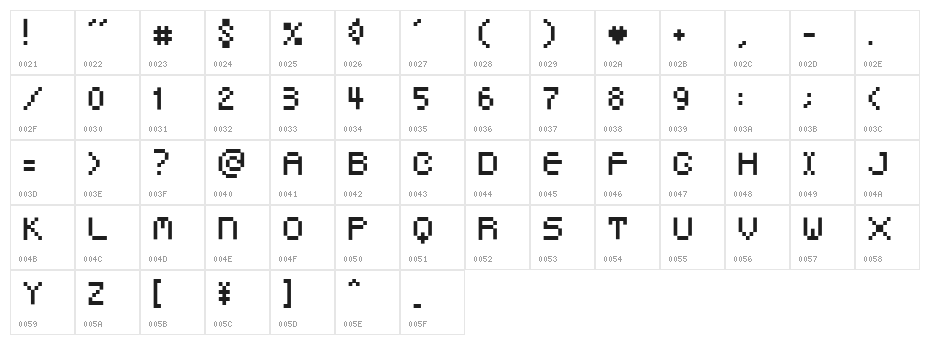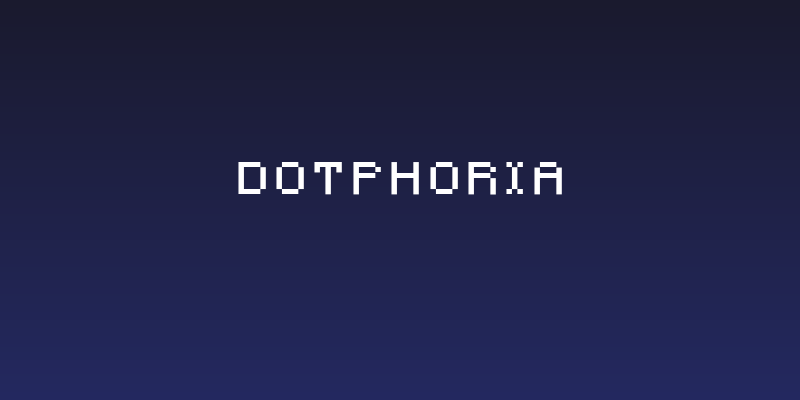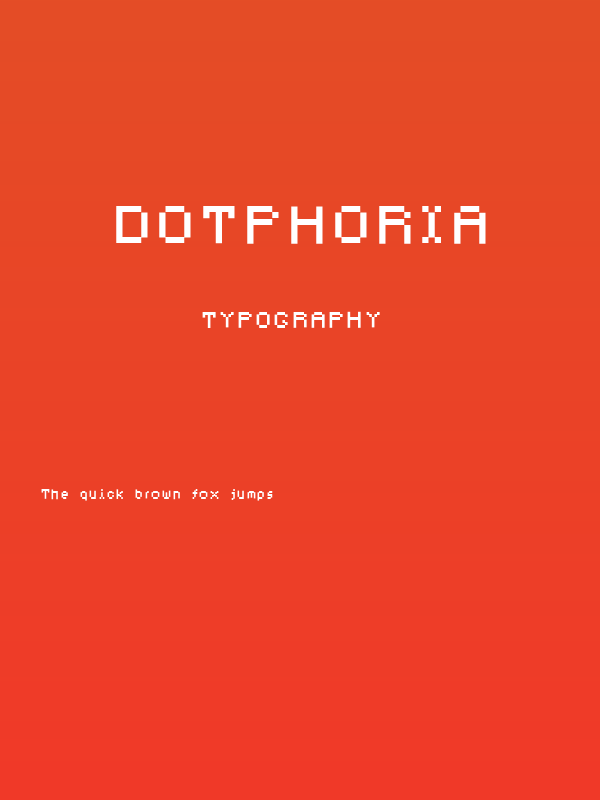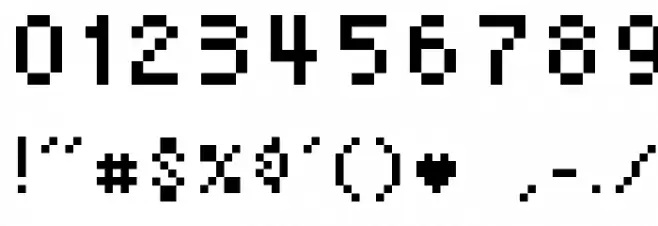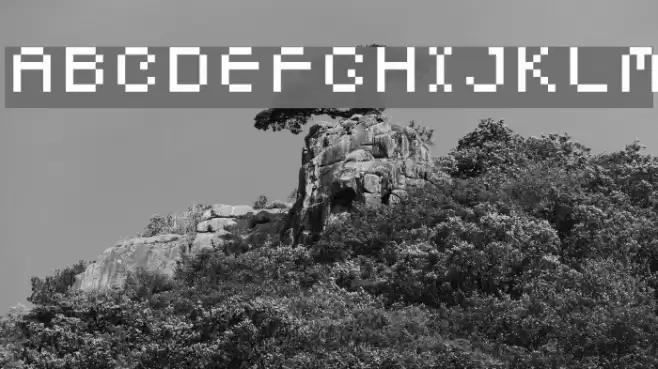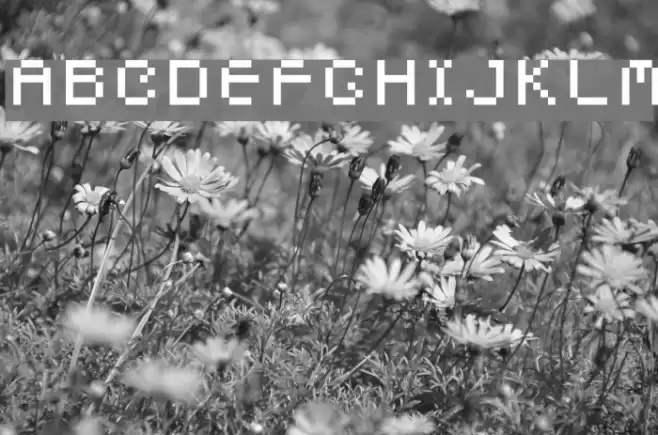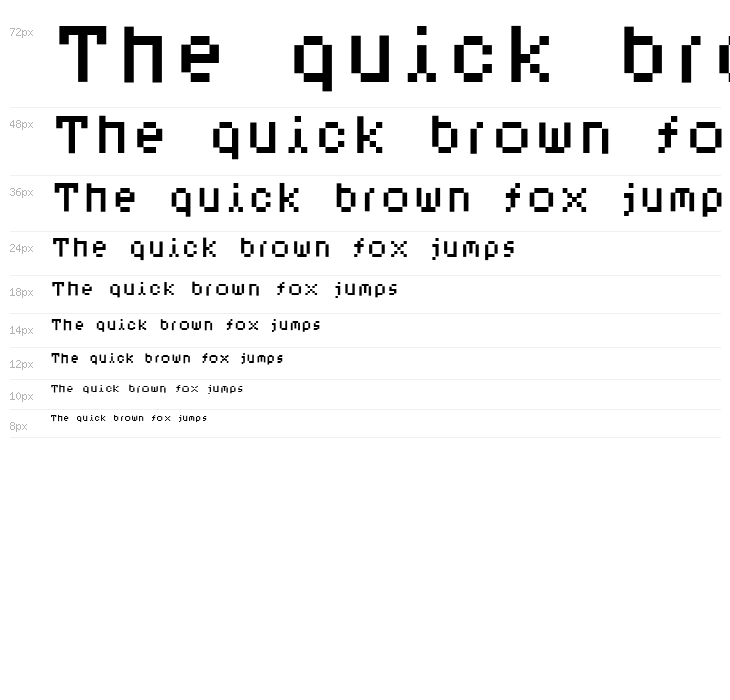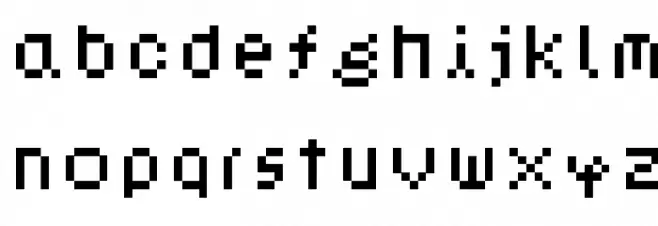
Dotphoria Font
| Style général | Retro, Digital |
| Cas d'utilisation | Logos, Posters, Digital Art |
| Projets proposés | Ideal for retro video game designs, tech-themed posters, digital art projects, and nostalgic branding. |